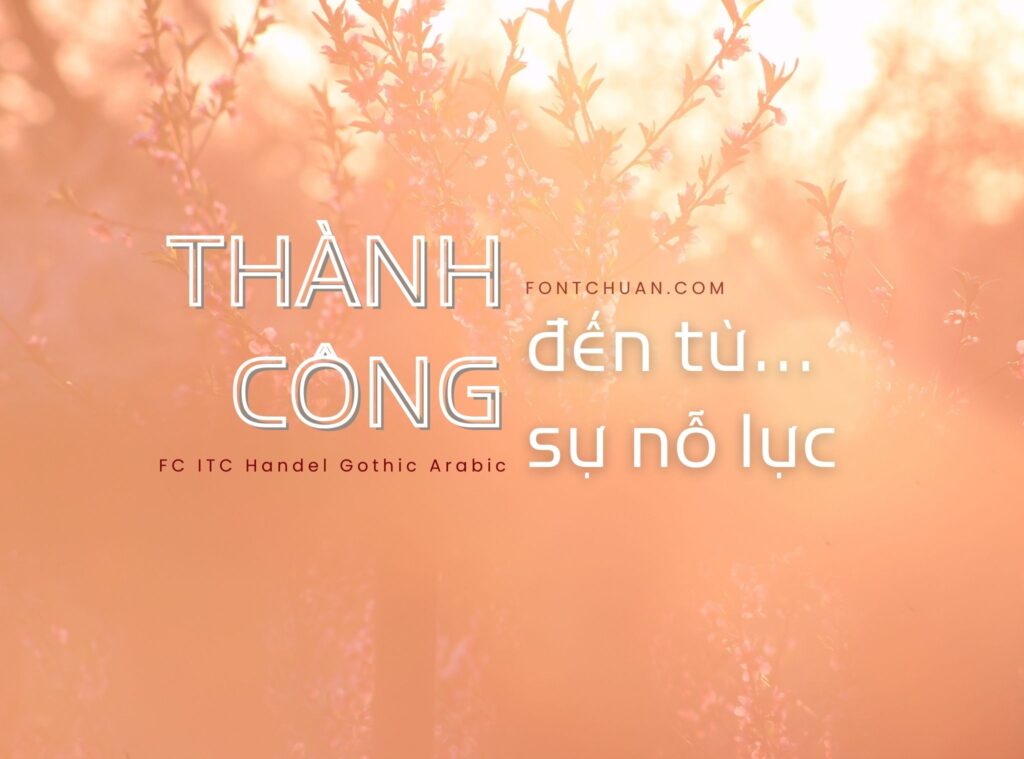
Font FC ITC Handel Gothic Arabic Việt Hóa
Tác giả Font: Rod McDonald, Nadine Cahine
ITC Handel Gothic Arabic là một biến thể của font chữ sans-serif hình học Handel Gothic, được thiết kế ban đầu vào năm 1965 bởi Donald J. Handel. Phiên bản Arabic này được phát triển bởi Nadine Chahine vào năm 2015, dựa trên phong cách chữ Kufic truyền thống, mang lại sự kết hợp hài hòa giữa thiết kế hiện đại và di sản văn hóa Ả Rập. Font này hỗ trợ tiếng Ả Rập, tiếng Ba Tư, tiếng Urdu và hơn 40 ngôn ngữ Latin khác, mở rộng phạm vi ứng dụng cho nhiều dự án quốc tế. Đồng thời, với thiết kế linh hoạt, font này có thể trở thành một Font Lễ hội để trang trí các ấn phẩm sự kiện vui tươi, hoặc được dùng như font ngày nhà giáo Việt Nam trong các thiệp mừng, poster và banner chúc mừng ngày lễ đặc biệt.
Với cấu trúc chữ sắc nét, độ dày đồng nhất và các đường nét tinh tế, Font FC ITC Handel Gothic Arabic phù hợp cho các thiết kế logo, tiêu đề, thương hiệu và các ấn phẩm quảng cáo khác. Đặc biệt, font này thích hợp cho các ngành nghề như quảng cáo, thiết kế thương hiệu và lĩnh vực truyền thông, nơi cần sự kết hợp giữa thẩm mỹ hiện đại và chức năng.